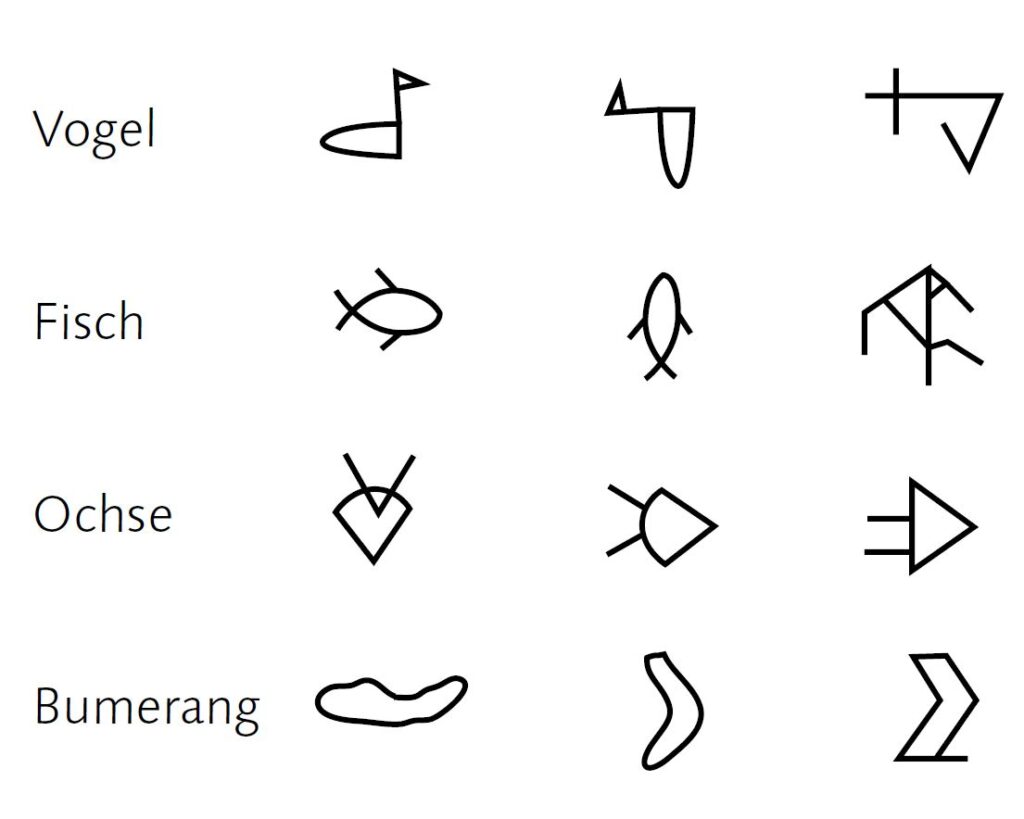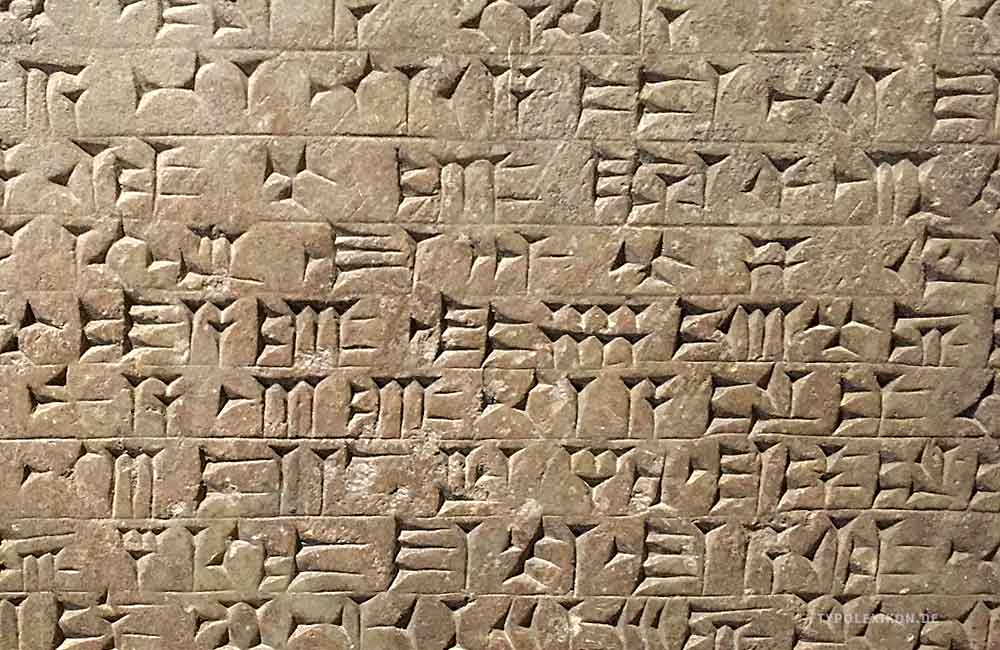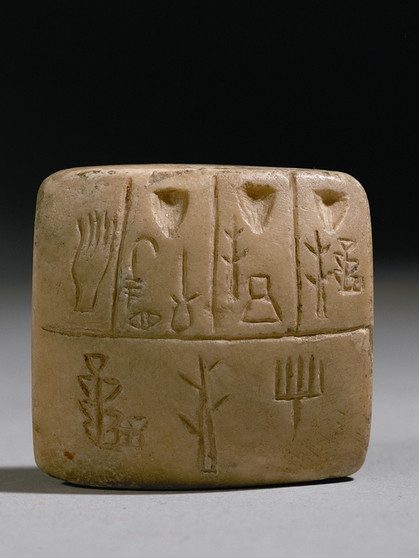
4000 – 3500 v. Chr.
Die ersten konkreten Ansätze einer Schrift werden mit den Sumerern 3500 v. Chr. in Mesopotamien. zusammengebracht. Hier taucht auch der Begriff Keilschrift zum ersten Mal auf. Dabei handelt es sich um eine Bilderschrift, die aus Piktogrammen und Ideogrammen besteht. Sie mündet im Laufe der Zeit über die Silbenschrift in eine Konsonantenschrift und lebt im alten Orient über mehr als zwei Jahrtausende weiter.
Mit einem Griffel in feuchten Ton gedrückt, entwickelte sie sich von Bildzeichen zu einem System aus Silben- und Begriffsschrift. Bei den Sumerern stand die klare, standardisierte Form für Verwaltung und Dokumentation im Vordergrund. Die Assyrer übernahmen und verfeinerten sie, nutzten sie in Archiven und Inschriften und gaben ihr monumentale Wirkung zur Darstellung von Macht und Autorität.